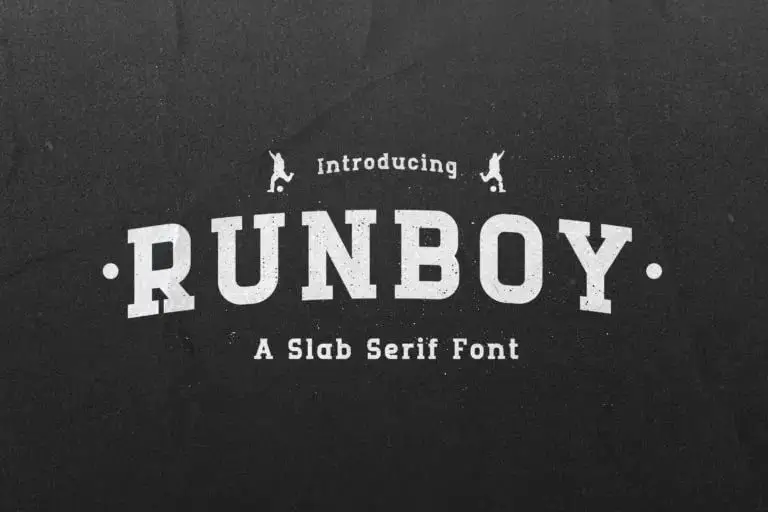
A Runboy Slab Serif é uma elegante fonte serifada robusta que oferece flexibilidade para diversificadas aplicações gráficas. Com sua arranjo meticuloso e belo dos caracteres, esta tipografia vai se destacar tanto em projetos formais quanto informais. Perfeita para headline ou logotipos, a Runboy Slab Serif inspira-se no estilo de fontes de fim de século 19 que utilizam serifas robustas e uma aparência duradoura. Adaptable para variedades de necessidades gráficas, esta fonte foi criada por um designer chamado Type Factory. Seu design elegante e sofisticado faz dela uma escolha atraente para qualquer tipo de projeto visual, como capas de livros ou rótulos porta-objetos. Inspirada nos padrões do fim do século 19, a Runboy Slab Serif exibe serifas robustas e um ar de confiabilidade que se destaca em design sofisticado e no design mais simples da moda contemporânea.